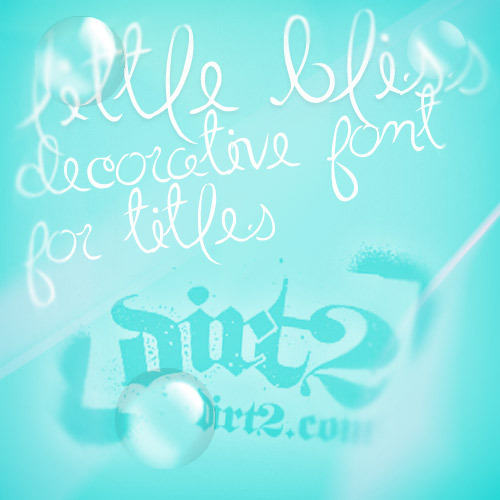
Little Bliss, progettata da Dirt2.com, è un font corsivo manoscritto gratuito caratterizzato da anse alte e finemente tracciate, salite ripide e un'aria elegante e alla moda. Le sue lettere strette scorrono in un gesto rapido e continuo.
Gli inviti di nozze sono il suo contesto ideale, poiché i tratti ampi e i ricchi fregi ricordano una grafia personale pur mantenendo l'aplomb composto della calligrafia formale. Le stesse forme leggere e allungate si adattano al branding di boutique, al packaging di cosmetici di lusso e agli editoriali di moda, dove il lettering può richiamare linee di nastri sottili o delicate illustrazioni a inchiostro.